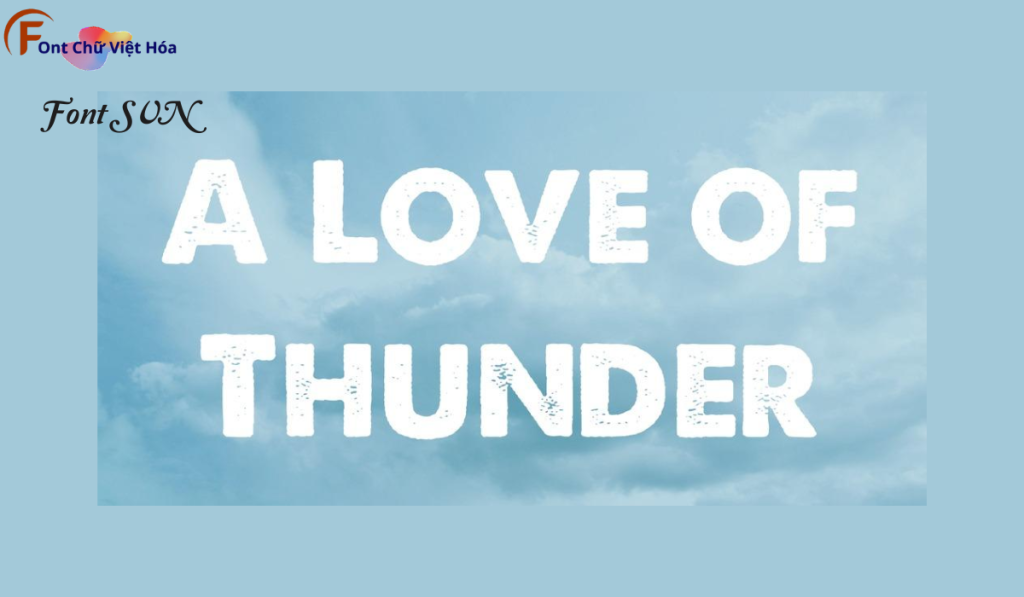
Font SVN A Love Of Thunder Việt Hóa
Phân loại: Cá tính, Độc đáo, Mạnh mẽ
Độ dày: Mỏng, Thường, Đậm
Font SVN A Love Of Thunder Việt Hóa là một font chữ không chân cá tính, thuộc bộ font SVN. Được thiết kế với mục tiêu mang lại sự độc đáo và sáng tạo, font này lý tưởng cho các dự án thiết kế như logo, poster, và bao bì sản phẩm. Với các nét chữ sắc nét và độ dày đều đặn, Font SVN A Love Of Thunder Việt Hóa không chỉ dễ đọc mà còn tạo cảm giác hiện đại và phá cách. Việc Việt hóa font giúp người dùng dễ dàng sử dụng trong các thiết kế tiếng Việt, mang lại sự tiện lợi và thẩm mỹ cao.